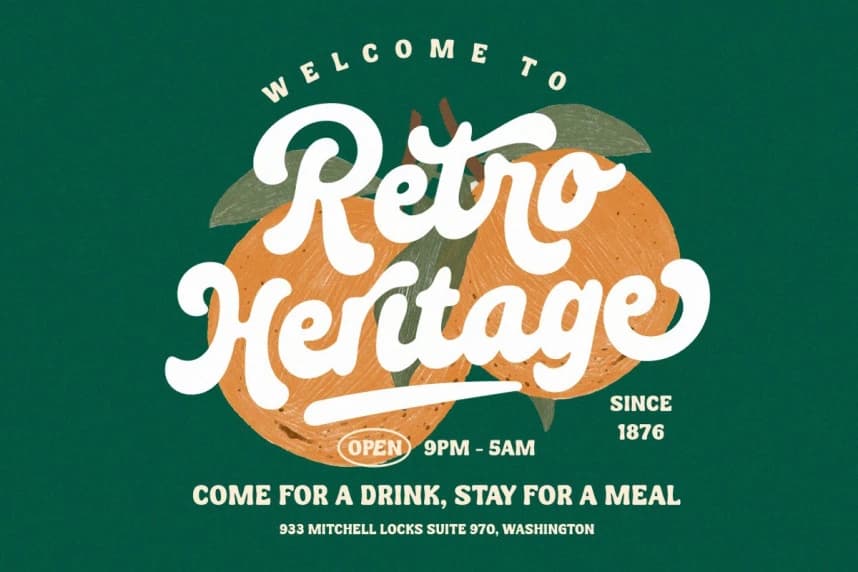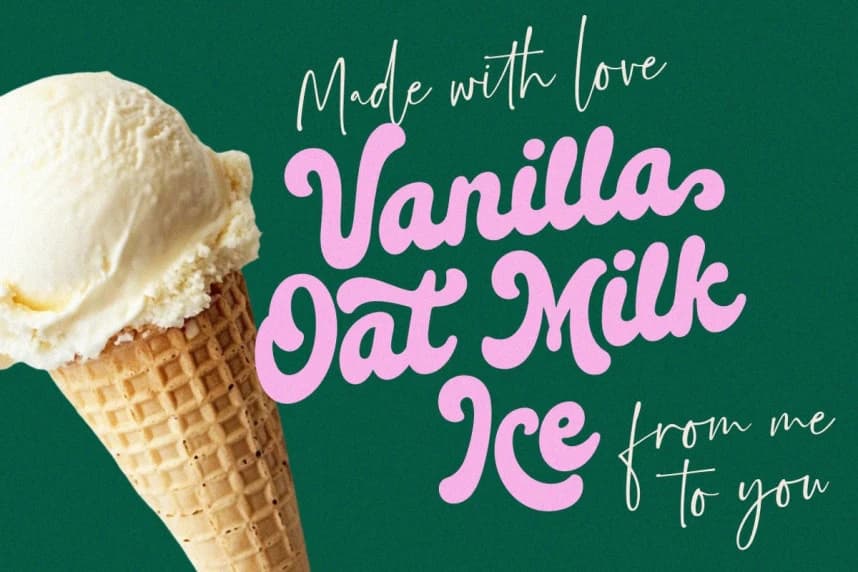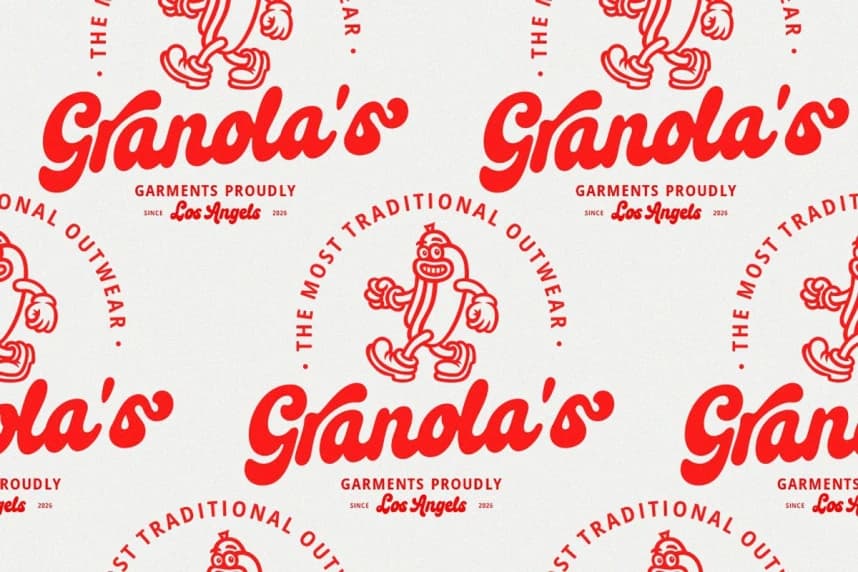
Bright Miracle Font - Tasarımlarınıza zahmetsiz çekicilik katın; bu retro-modern script fontu, nostaljik hisleri taze, çağdaş bir dokunuşla birleştirir. Akıcı eğriler, doğal akış ve rahat bir el yazısı hissiyle tasarlandı.
Bright Miracle Font - Tasarımlarınıza zahmetsiz bir çekicilik katın; bu retro-modern el yazısı fontu, nostaljik bir hava ile taze, çağdaş bir dokunuşu bir araya getirir. Pürüzsüz eğriler, doğal akış ve rahat el yazısı hissi ile tasarlandı.